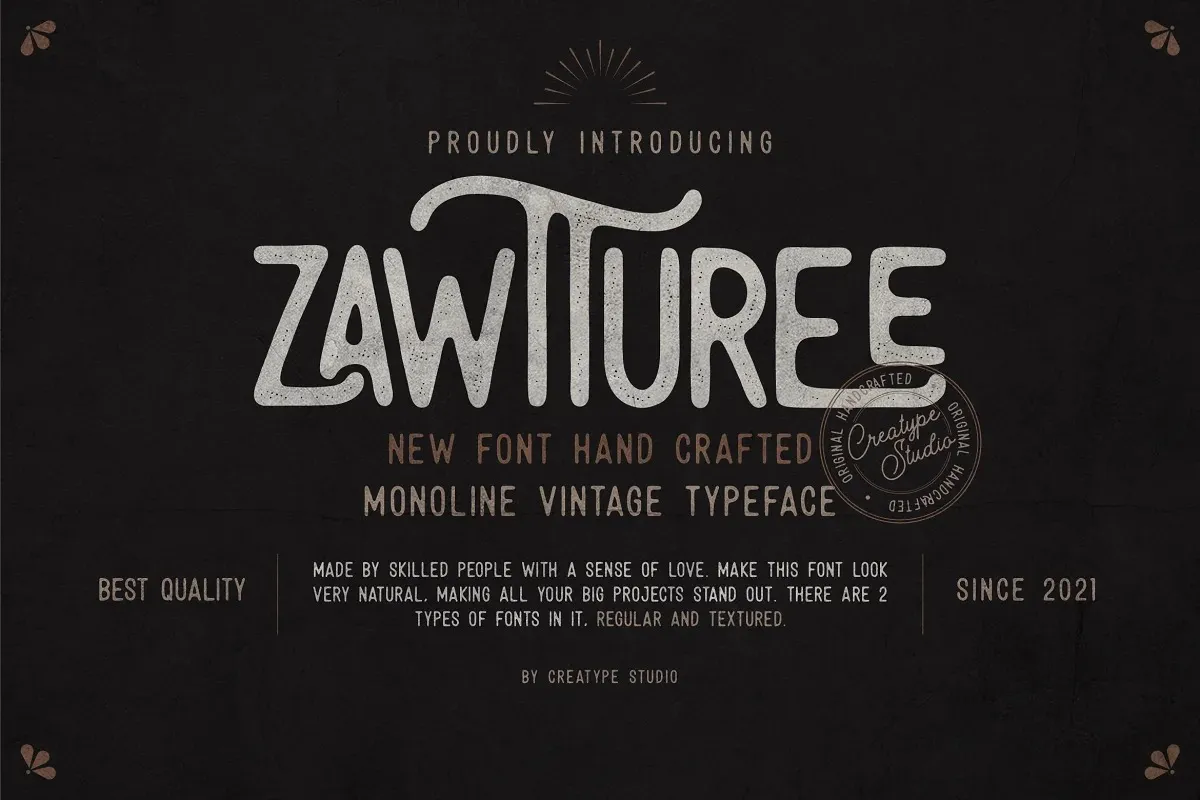
Zawtturee Font – Download Grátis
Zawtturee é uma fonte mono-linha criada pelo designer Elvian Andreani que se destaca por suas características semelhantes a canetas marcadoras, apresentando textura autêntica e um look casual e vintage. Esta font oferece dois tipos de estilos: o regular e o com textura, fazendo-a perfeitamente adequada para seus trabalhos maiores. Seu estilo natural é tão impressionante que sua letra consegue destacar seu projeto em meio aos demais. Ideal tanto para projetos profissionais quanto pessoais, Zawtturee surge como uma opção de font ideal para aqueles procurando algo único e atraente no seu próximo projeto visual. Seu design criado pelo 99designs é perfeito para destacar seus trabalhos, transformando-os em obras que chamam atenção.